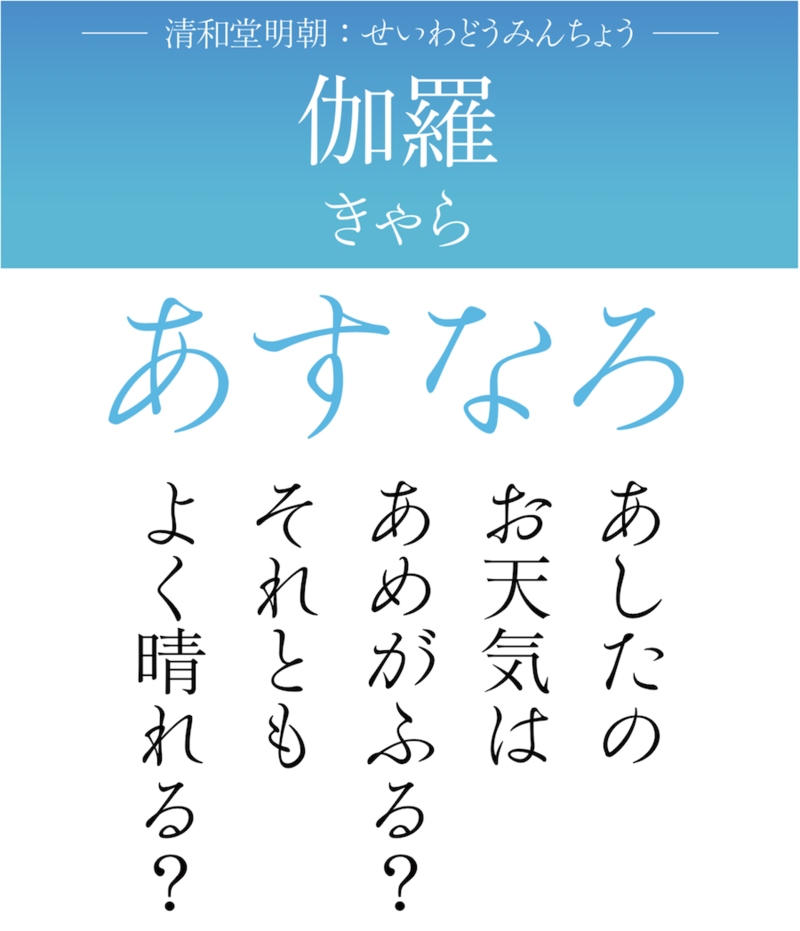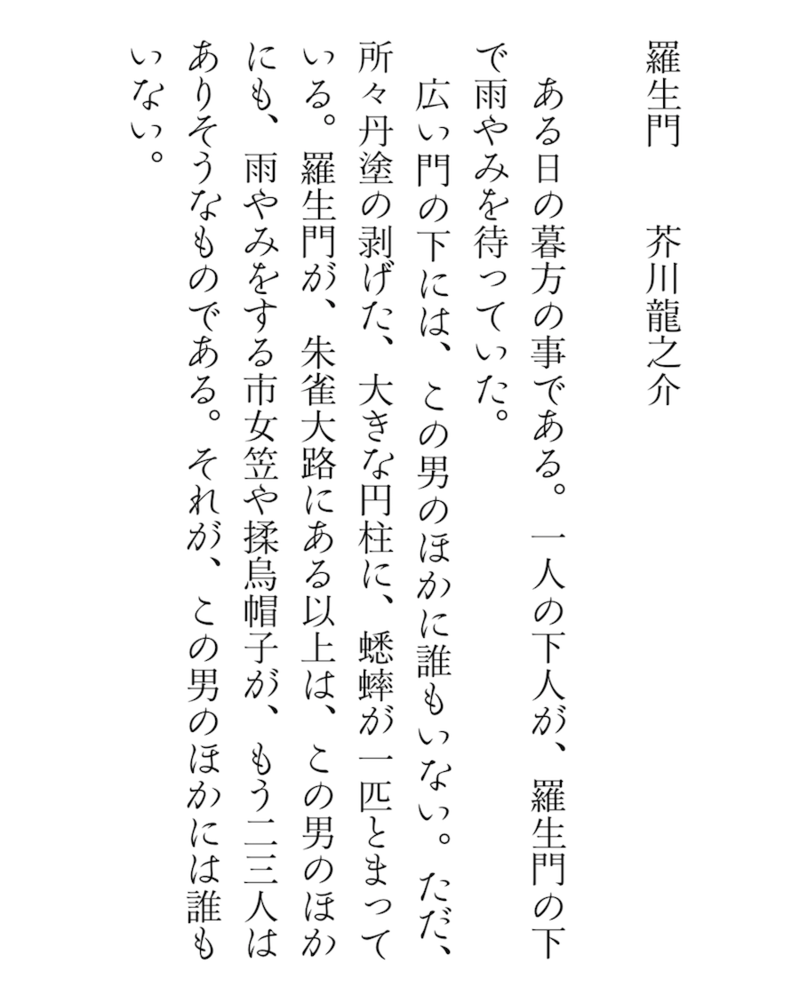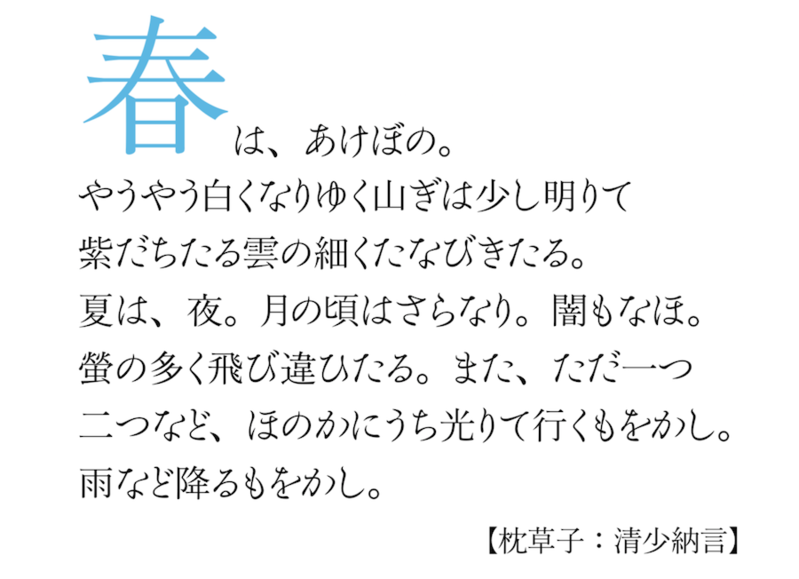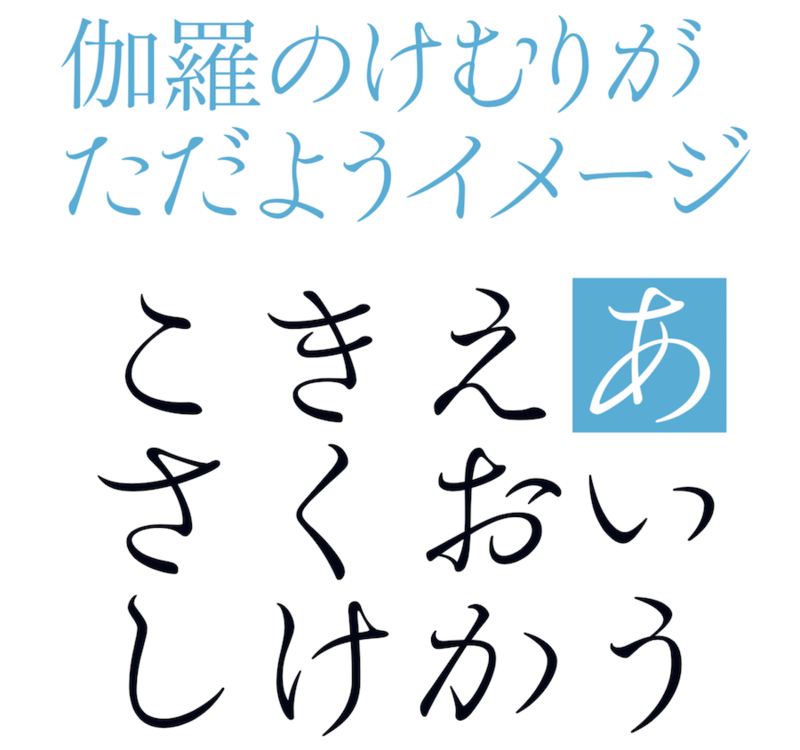
清和堂明朝体 伽羅仮名バージョン。
高級香木「伽羅」の薫り高い優雅なイメージを表現。
・仮名は、プロポーションに加え、ペアカーニングを搭載。
・OpenType機能で、固有の文字幅と適切な字間で組むことができます。
・伽羅の仮名は今までの明朝体とは一味違った、とっても個性的なエレメントです。
・プロポーションでも字間が空いてしまう文字の組み合わせにペアカーニングを設定。
・伽羅は全ての文字の組み合わせにペアカーニングが設定されています。